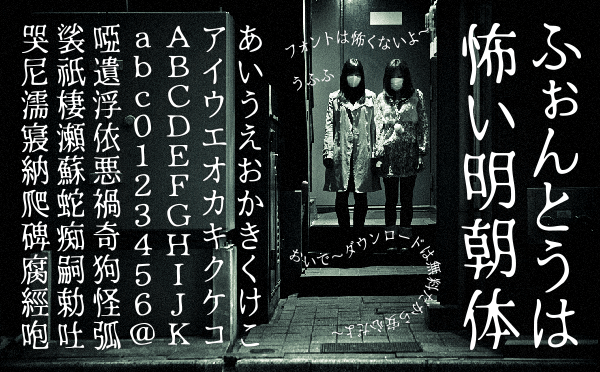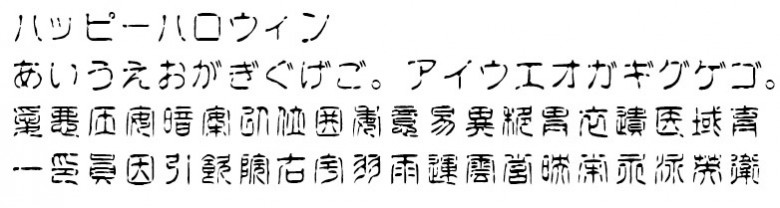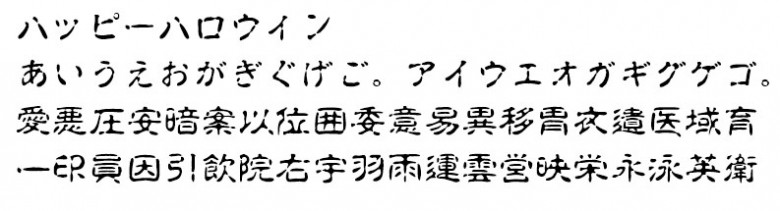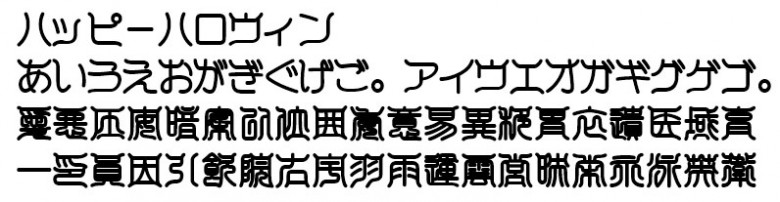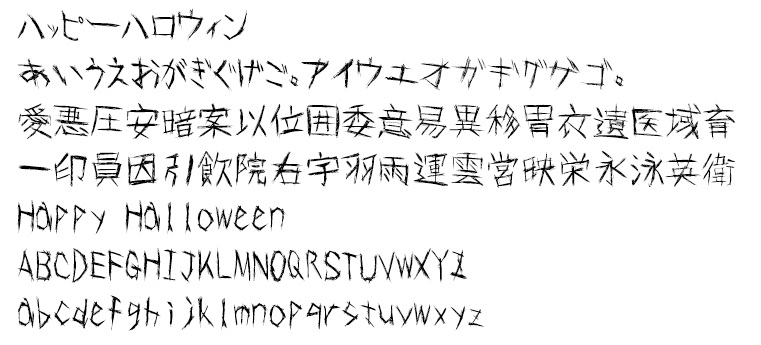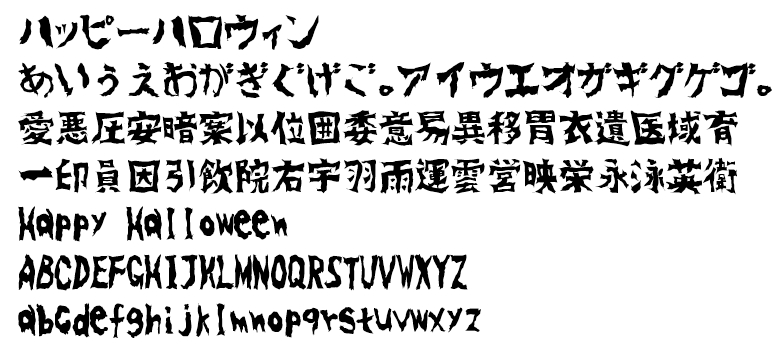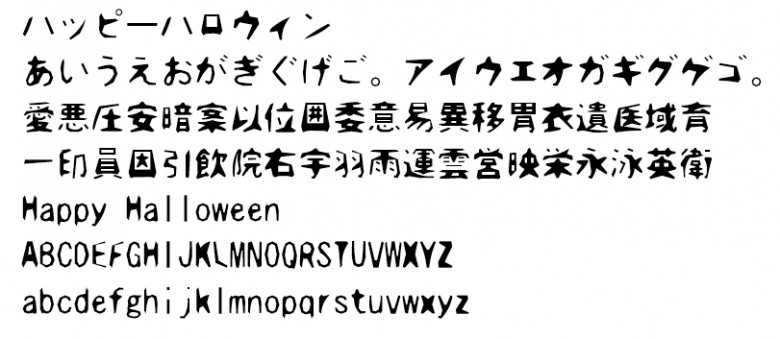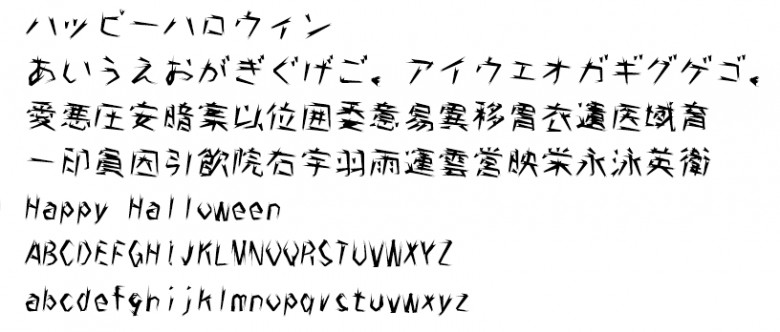
10月31日は怖い怖いハロウィンですね。
そんな怖~いハロウィンに向けて、何か日本語が使えてハロウィンに似合う恐ろしげなフォントってあるのかな~、なんて色々探してるあなた。それが色々あるんです。
おどろおどろしいものから、すさんだフォント、淡々としてて逆に怖いフォントなどなど、しかも無料で商用利用もOKときてます。
フォントを作ってる方々には本当に頭が下がる思いですが、ひらがな、カタカナ、漢字まで使えちゃう、というフォントが沢山あるんですね。
あなたの求める怖さに似合ったホラーフォント、ありますか? ^-^)
ふぉんとうは怖い明朝体
白舟書体
- 白舟篆古印教漢
ホラーフォント「怨霊」
ホラーフォント「吐き溜」
ザクザク切った感じの切り絵風フォント「切絵字」
すさんだ感じ、尖った感じの「イバラ字」
淡々とした怖さ「あずきフォント」
あなたの求めるハロウィンに似合う怖い怖いホラーフォント、ありましたか?
私などは、文字を見ただけで怖いです。
自分で選んでおきながら、あまり見たくない気が ...